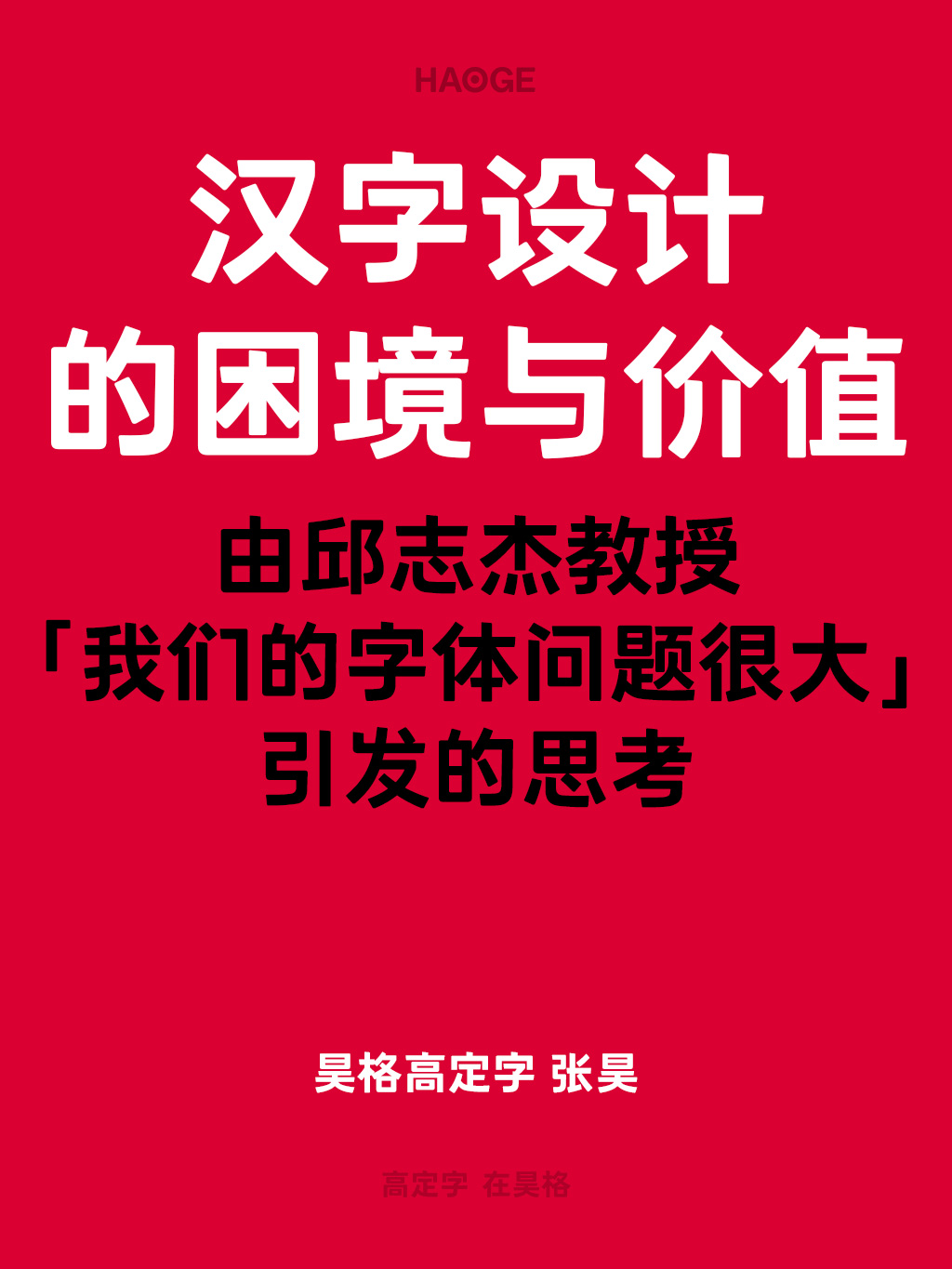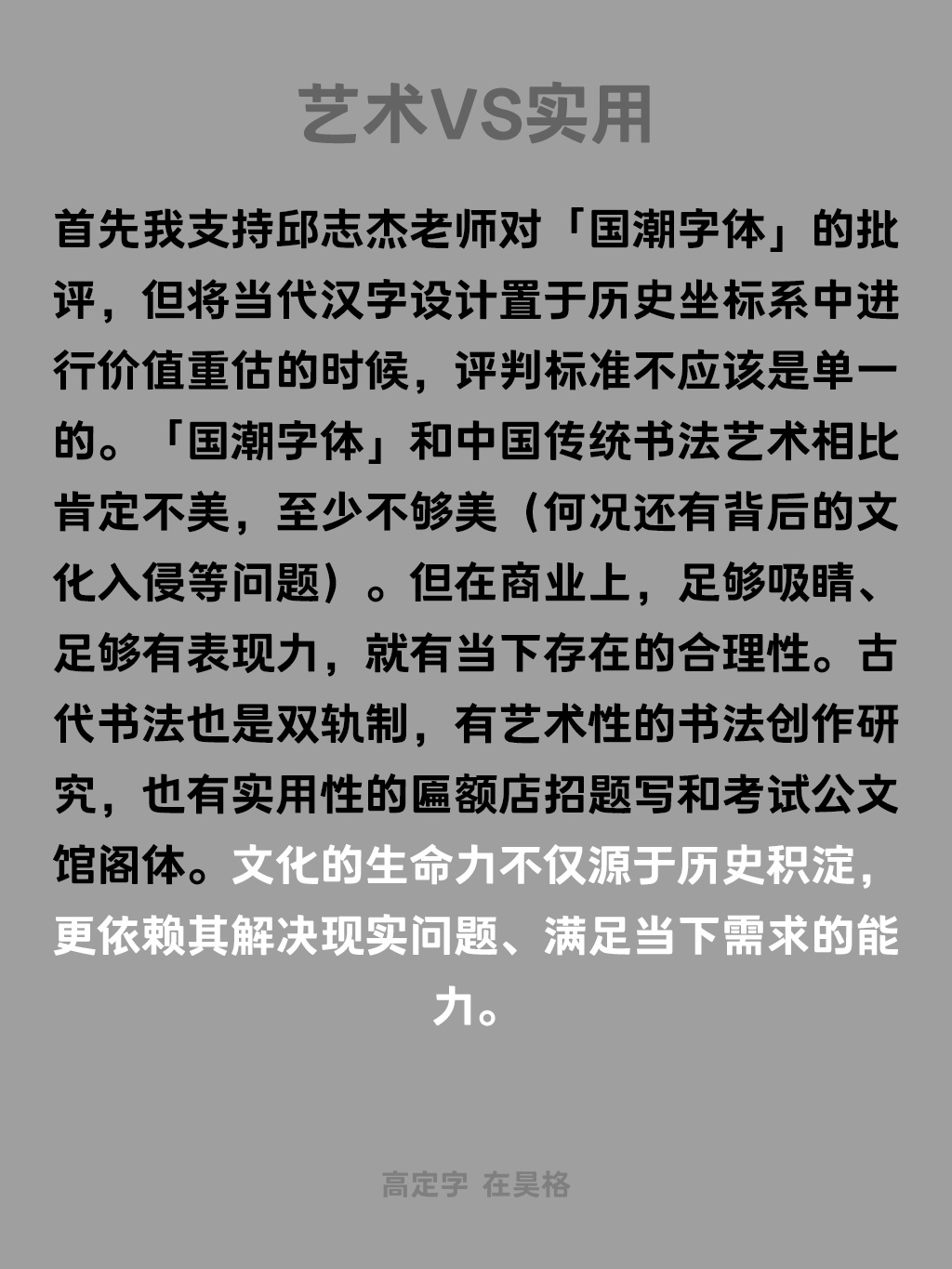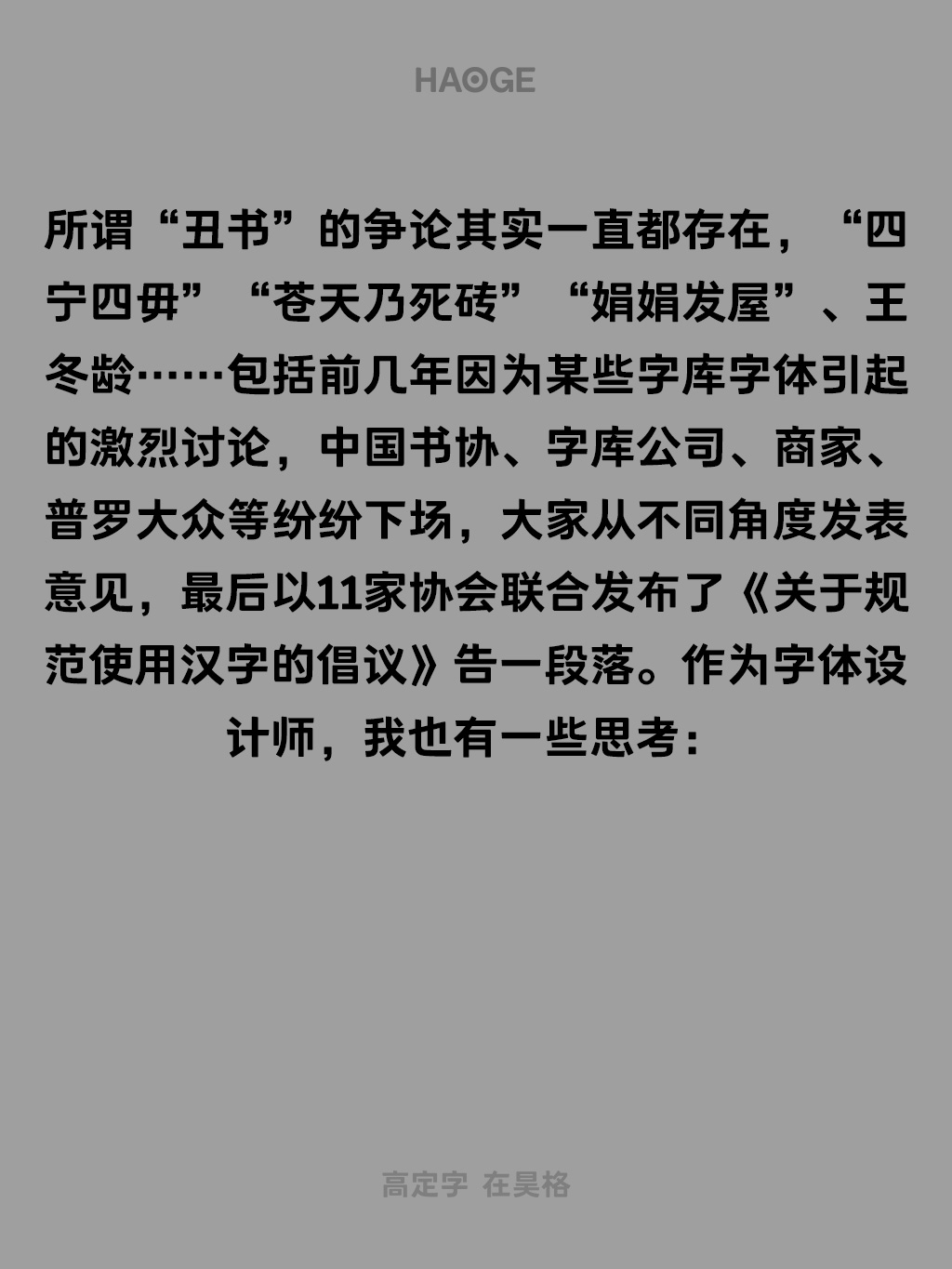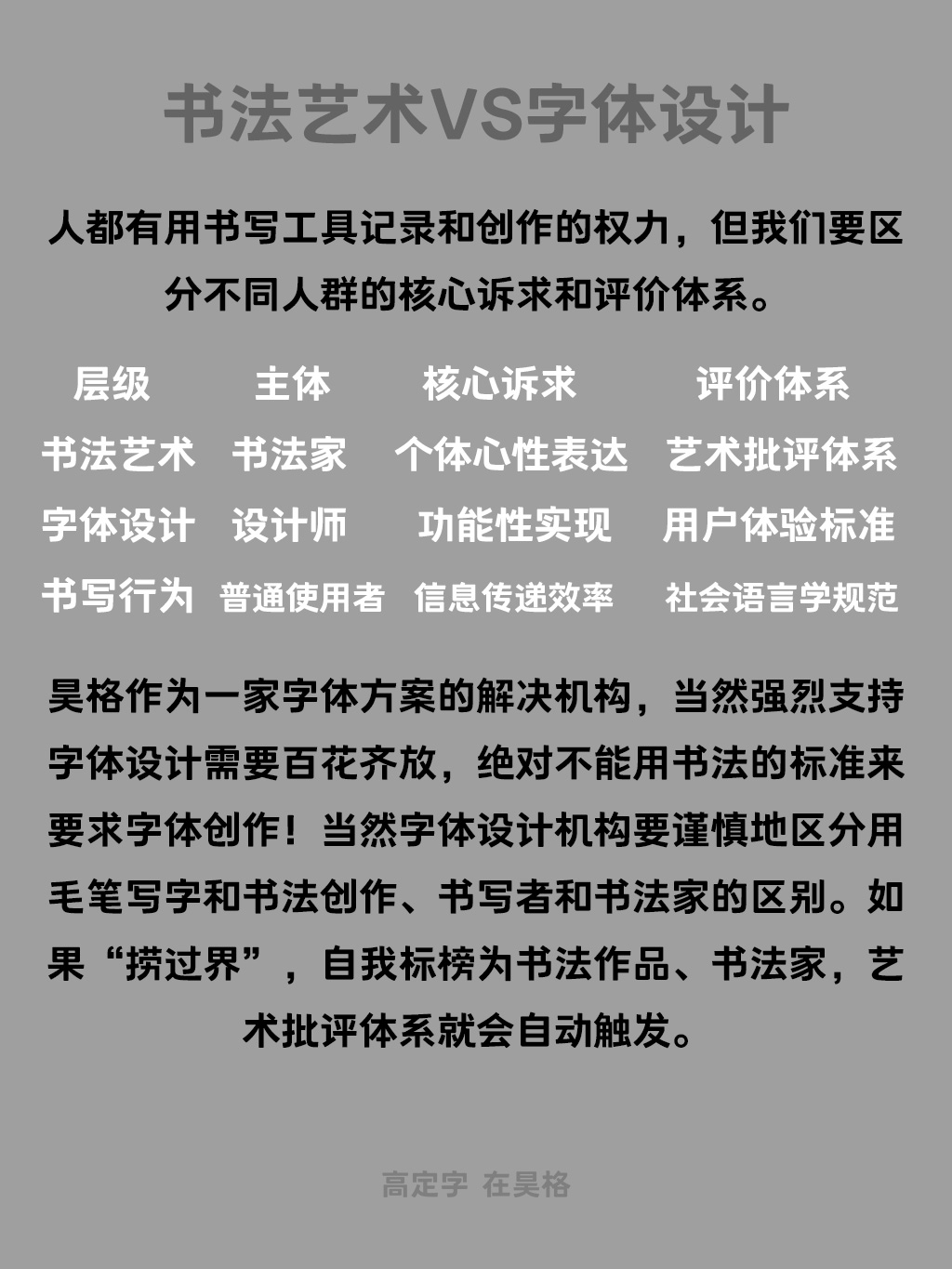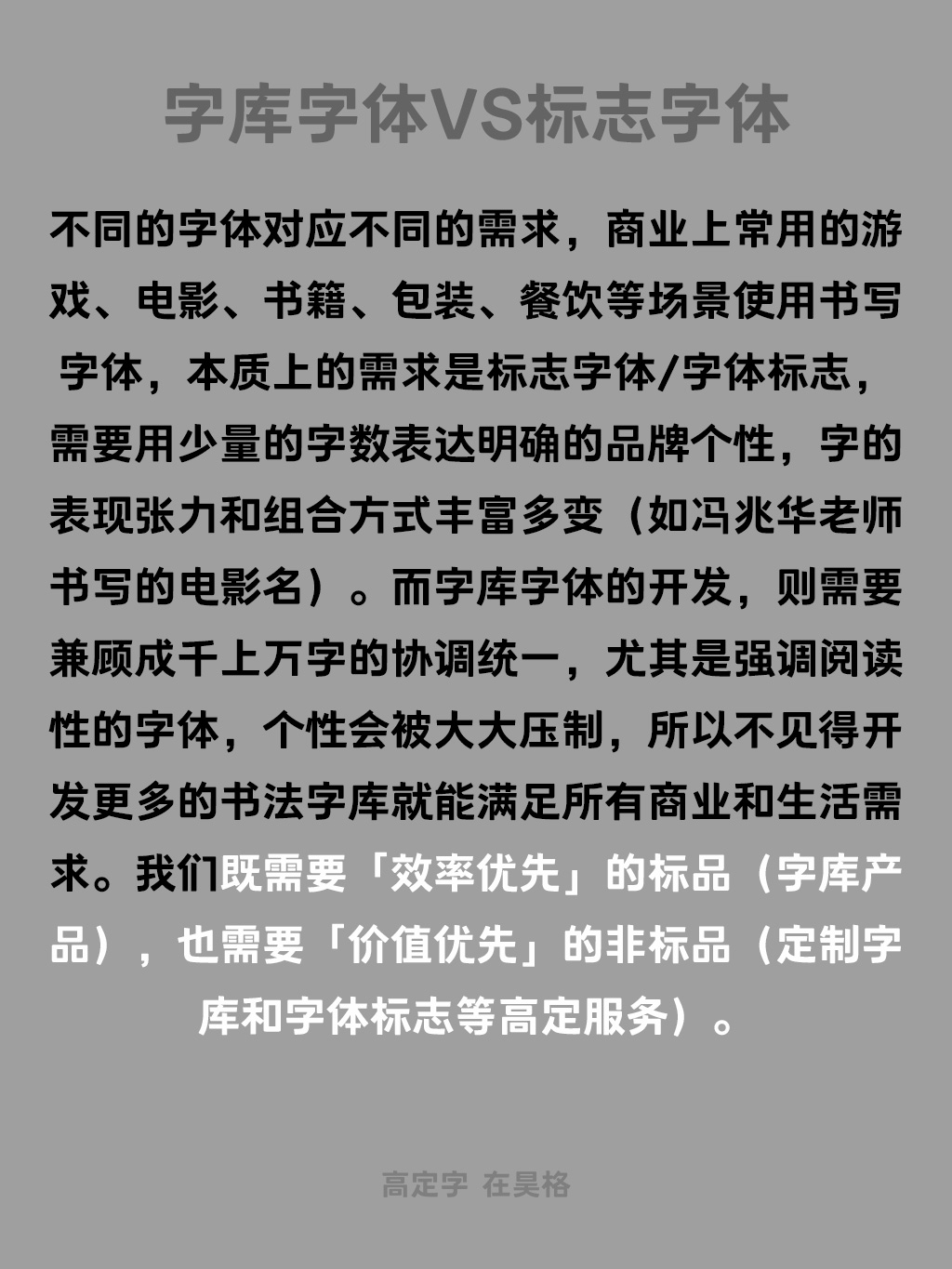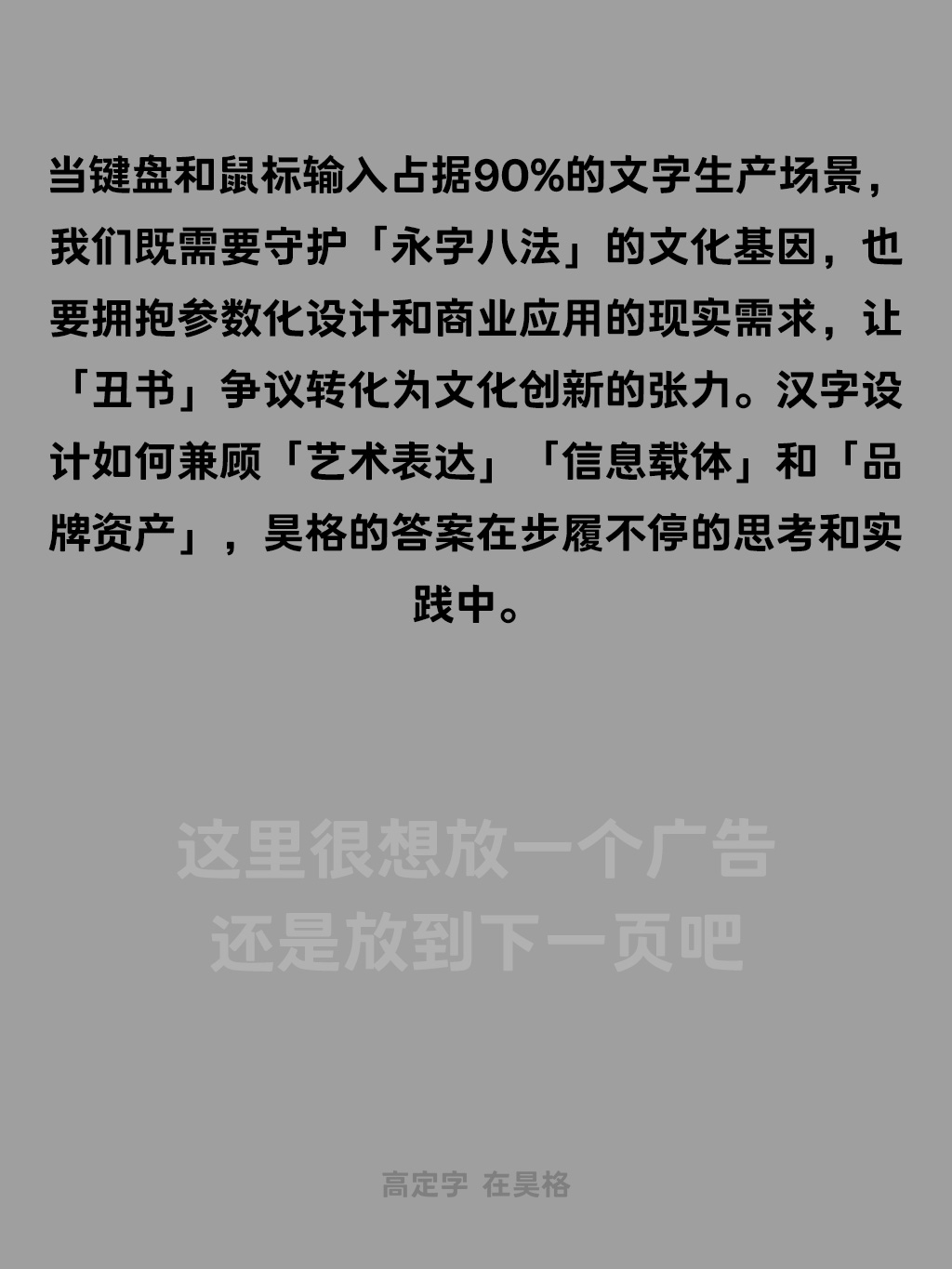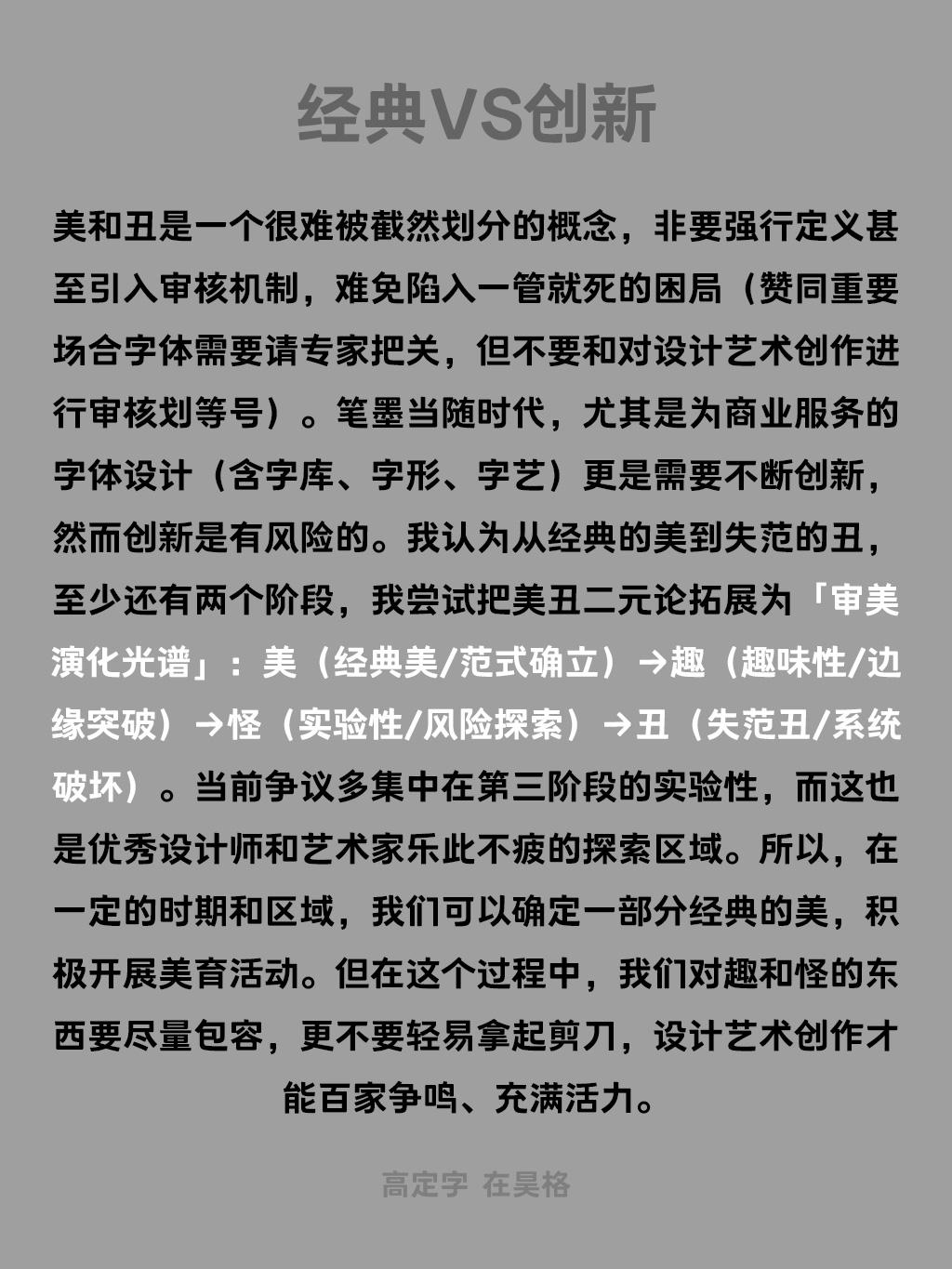
汉字设计的困境与价值——由邱志杰教授「我们的字体问题很大」引发的思考
汉字设计的困境与价值
——由邱志杰教授「我们的字体问题很大」引发的思考
昊格高定字 张昊
天津美院邱志杰教授最近有段视频很火,他说,我们的字体现在问题很大,引发了热议。
对此,昊格高定字艺术总监张昊写了一篇《汉字设计的困境与价值》的小文回应,
在社交媒体上受到了字体圈和平面设计圈的热烈讨论。